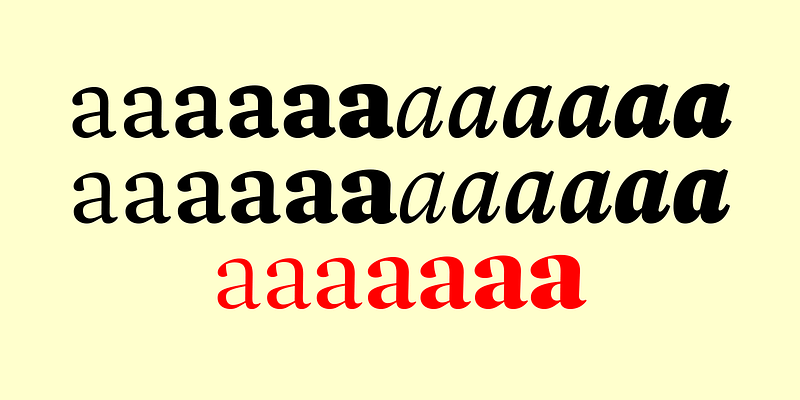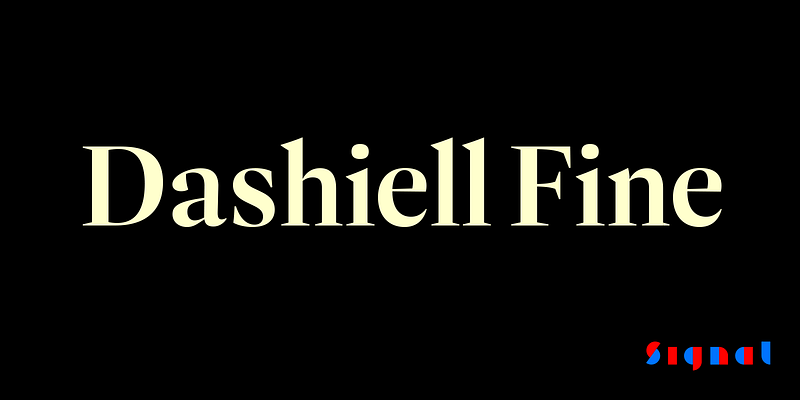
Le contraste dramatique et les lignes de cheveux du Dashiell Fine sont meilleurs dans les grands formats, où ses empattements en lames et ses formes dérivées du Caslon lui confèrent une élégance dure et Didonesque. Ses sept graisses comprennent un style Light supplémentaire pour les travaux particulièrement délicats ; sa graisse Black apporte une touche d’élégance.